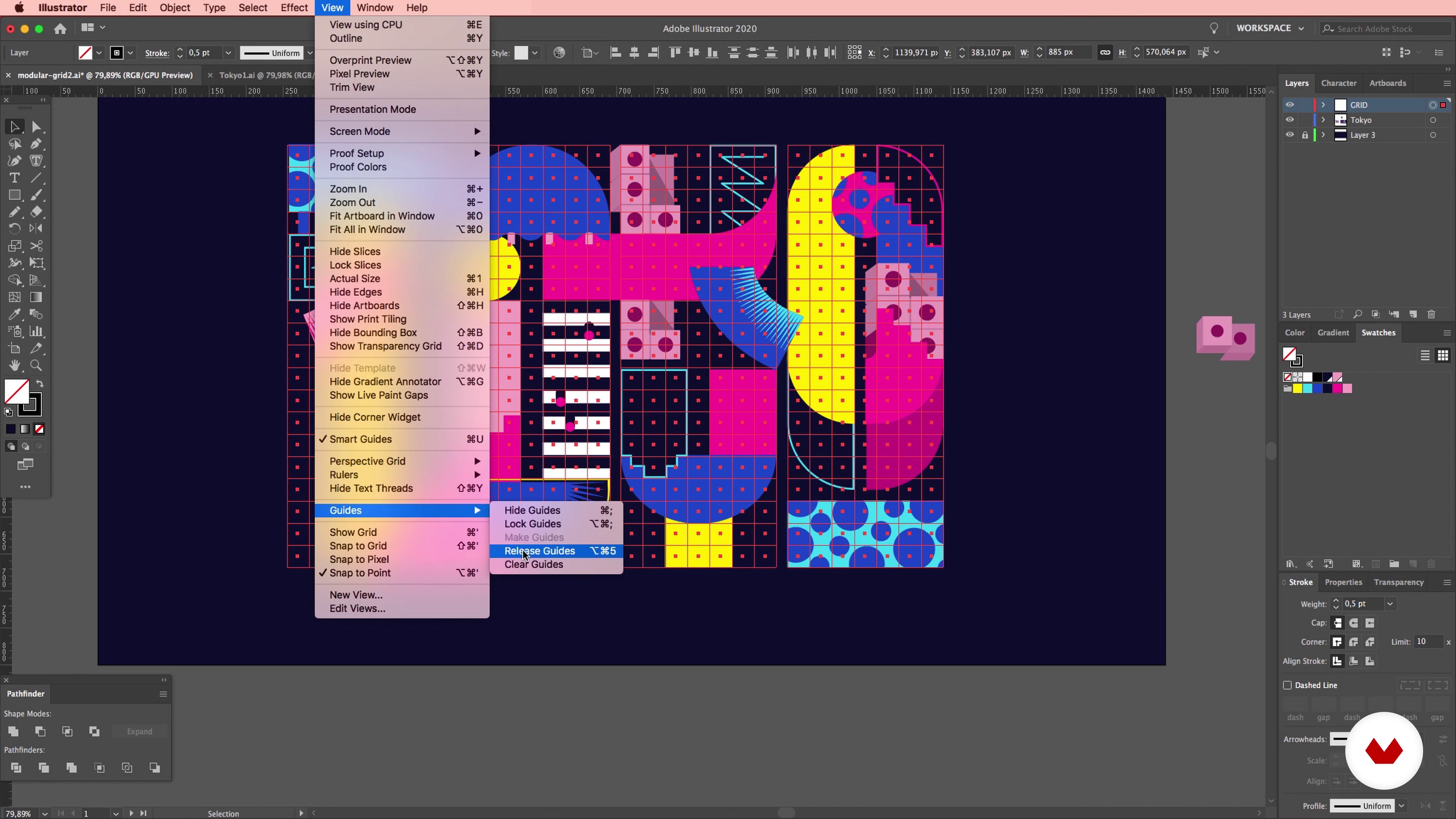
Combineer illustratie, typografie en kleur
Over de videoles: Combineer illustratie, typografie en kleur
Samenvatting
“Zodra we genoeg elementen hebben, gaan we beginnen met het samenvoegen van de verschillende elementen met het type. Train je oog en ontdek welke vorm op welke typografische module lijkt. Houd in gedachten om de delicate balans tussen leesbaarheid en speelsheid te volgen.”
In deze videoles behandelt Birgit Palma het onderwerp: Combineer illustratie, typografie en kleur, dat deel uitmaakt van de online cursus van Domestika: Geïllustreerde digitale belettering maken. Leer woorden diepte en betekenis geven met vorm, kleur en volume.
Gedeeltelijke transcriptie van de video
“Combineer illustratie, typografie en kleuren In deze les gaan we alle verschillende elementen samenvoegen. Het is belangrijk om je oog te trainen om te zien welke vormen bij welke illustraties passen. Dus hoe passen illustraties, typografie en kleur bij elkaar? Dat zoeken we uit. Wat ik zie is dat het dak van het traditionele heiligdom is een beetje hetzelfde als deze curve op de zaak. De vraag zal zijn hoe we dat kunnen gebruiken, incorporeren, een of twee keer om het modulaire type een beetje anders te maken. Wat ik ook zag is zoals deze traditionele Japanse elementen, die ze gebruiken in...”
Samenvatting van de cursus: Geïllustreerde digitale belettering maken